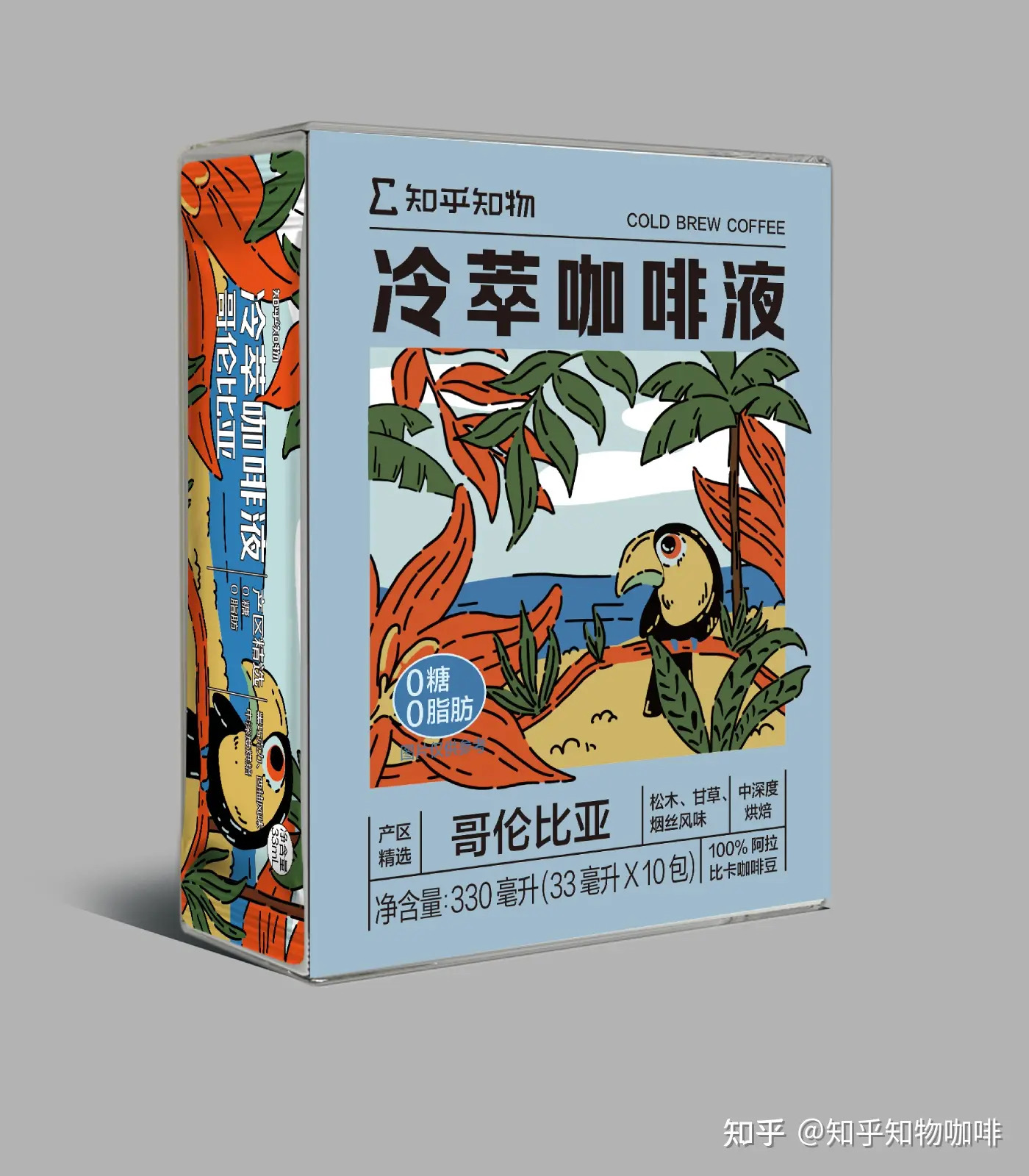
方正壹基金壹家人体
方正壹基金壹家人体 获2项设计大奖
仇寅,夏颖
创意字体、黑体
2021
方正壹基金壹家人体是由壹基金与方正字库联合开发的国内第一款公益品牌联名字体,以文字这一独特介质传播“壹家人”理念。这款字体不仅设计优美,适用于广告、包装等各类场景,而且字体售卖部分收入将用于壹基金的公益项目,帮助弱势群体改善困境。
方正壹基金壹家人体由方正字库设计总监仇寅带领团队设计,现代黑体融入了圆体与手写体的特点,新颖、独特的导圆处理和“喇叭口”设计、竖笔画使用了前倾2°的处理,在原本平稳的黑体上增添了书写意味,圆润饱满,凸显亲和友好的字体形象。
获奖情况
2021 GDC Award 铜奖
2021年,方正壹基金壹家人体荣获“2021 GDC Award 铜奖”
2021亚太年鉴 年度选择单元收录
方正壹基金壹家人体2021亚太年鉴 年度选择单元收录